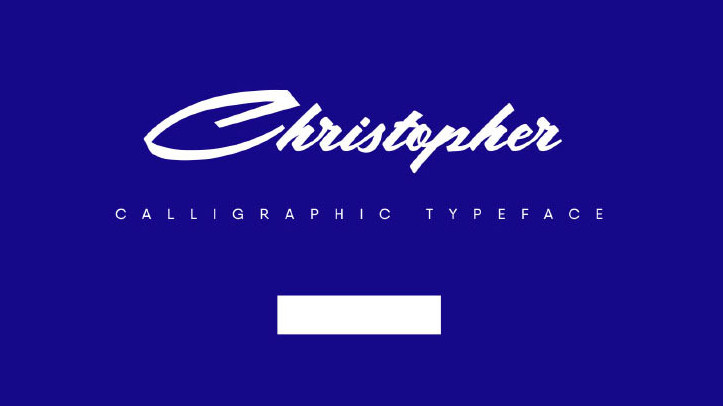
Christopher Calligraphy Font é uma tipografia feita por Hamilton com características de desenho à mão que combina elementos de letra maiúscula, minúscula, números e símbolos. Como mostrado nas ilustrações fornecidas, esse tipo de fonte se adapta perfeitamente para projetos como design de roupas, selos, logotipos, identidades corporativas e panfletos. Este é um recurso gráfico ideal para designers que buscam uma fonte elegante e personalizada para seus trabalhos visuais criativos. Seja você criando sua marca ou adicionando um toque de refinamento em projetos gráficos mais formais, Christopher Calligraphy Font fornecerá os elementos necessários para estilos arquitetônicos modernos e clássicos.